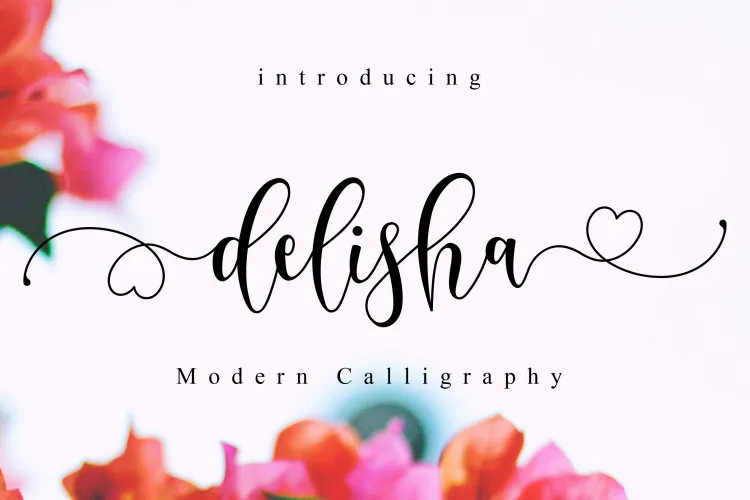
Delisha Script Font – Fonte Grátis
Delisha Script Font
A Delisha Script é uma fonte elegante e moderna que traz a beleza do script ao seu design. Introduzida pela Befonts como uma nova fonte de escrita modernizada, ela oferece um toque único e especial para seus projetos digitais. Esta fonte é perfeita para criar logos, identidades visuais, convites, cartões de visita, decorações para casamentos, postagens nas redes sociais ou qualquer outro projeto que precise de uma textura handwritten sofisticada. Delisha Script traz a essência da escrita artesanal em um formato digital, criando um efeito único e elegante. Ideal para designers buscando dar mais vida e personalidade a seus projetos digitais.